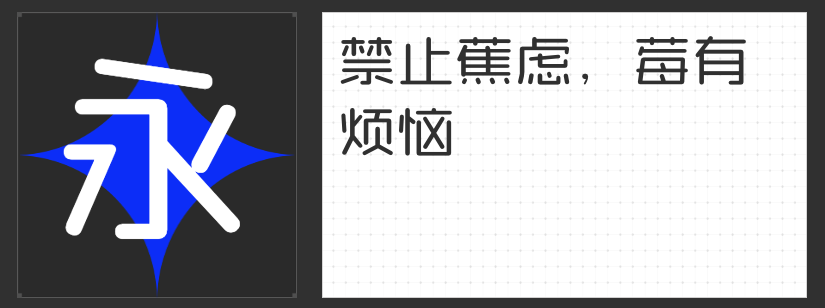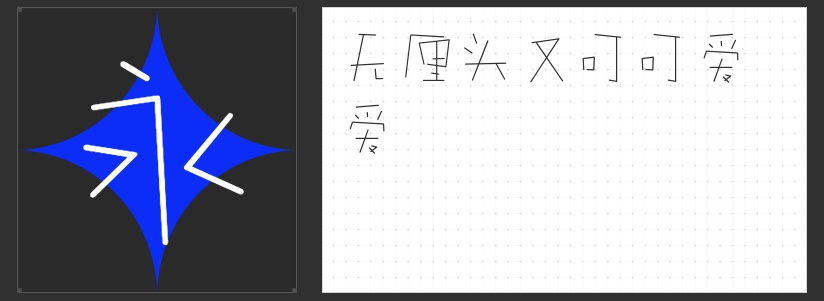
广告设计中的创意字体新宠:四款独特字型解锁视觉新维度
在广告设计的世界里,字体不仅是信息传递的载体,更是塑造品牌个性、激发情感共鸣的关键元素。以下四款各具特色的创意字体,以其独特的设计语言,为广告创意注入无限可能。
一、励字圆梦简 常规
这款字体以圆润柔和为基调,巧妙融合直线与圆弧元素,创造出外圆内方的视觉平衡。其笔画起止与转折处的自然圆弧处理,赋予字体温暖亲切的气质,而松散的中宫布局则让整体字形更显开阔舒展。这种刚柔并济的设计哲学,尤其适合需要传递人文关怀或科技温度的广告场景,能在理性与感性之间找到完美支点。
突破传统汉字结构的桎梏,这款字体以饼干棒的童趣意象重构字形逻辑。随意而不失章法的笔画分布,倒梯形字框与开口设计的巧妙运用,营造出无厘头式的可爱氛围。其颠覆性的设计思维,特别适合年轻化品牌或创意产品的视觉表达,能在瞬间抓住受众注意力,让广告信息在轻松诙谐中深入人心。
当圆体的温润邂逅黑体的稳重,这款字体在方正结构中注入灵动气息。通过精准控制的外圆角处理,既保持了黑体字固有的力量感,又消解了直角带来的生硬感。这种刚柔并济的特质,使其成为科技、金融等需要展现专业性与亲和力的行业广告的理想选择,在屏幕显示中更能凸显清晰锐利的视觉效果。
四、字恋狂漫野 鸣风
以手写质感为基底,这款直线字体通过张弛有度的结构布局与通透的布白空间,创造出富有韵律的视觉节奏。去钩处理与笔画断开的创新设计,在保持简洁性的同时赋予字体呼吸感。其均匀的灰度分布与自然的大小错落,特别适合需要营造文艺气质或自然风格的广告创作,让文字本身成为传递品牌态度的视觉符号。
这四款字体各具美学特质,从童趣想象到科技理性,从人文温度到艺术韵律,为广告设计师提供了丰富的创意工具箱。选择合适的字体,即是选择与品牌灵魂对话的语言,让每一次视觉表达都成为直击人心的艺术创作。